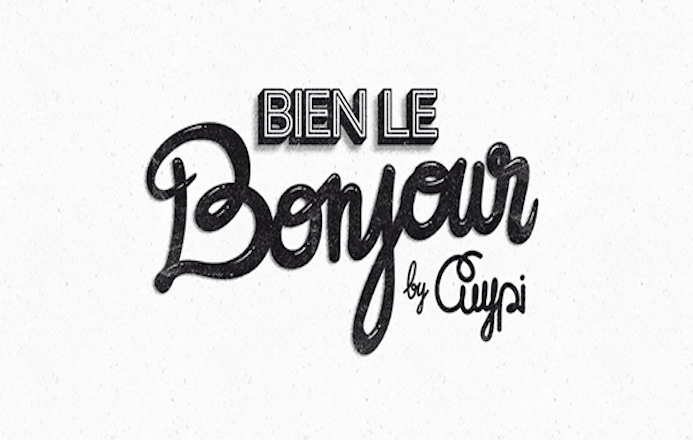
La typo, le handlettering et la calligraphie permettent tout et parfois même le vulgaire, comme cet exercice de style mené Sébastien Cuypers, directeur artistique à Paris.
Ces typographies reprennent des vulgarités assez courantes : bref, un exutoire sur fond rose pétant. Le décalage est détonant, et Le Papier adore !